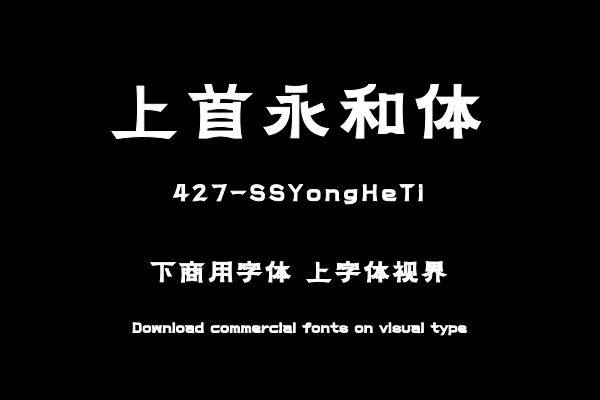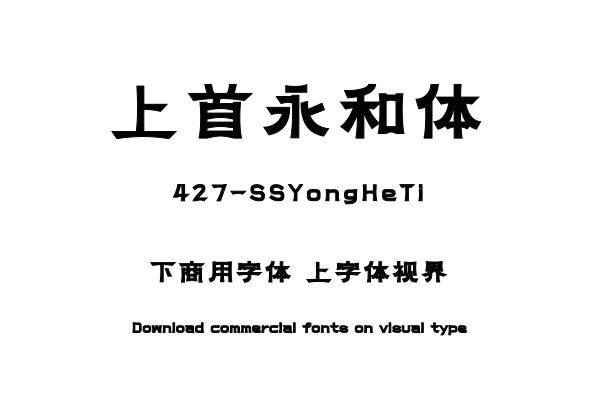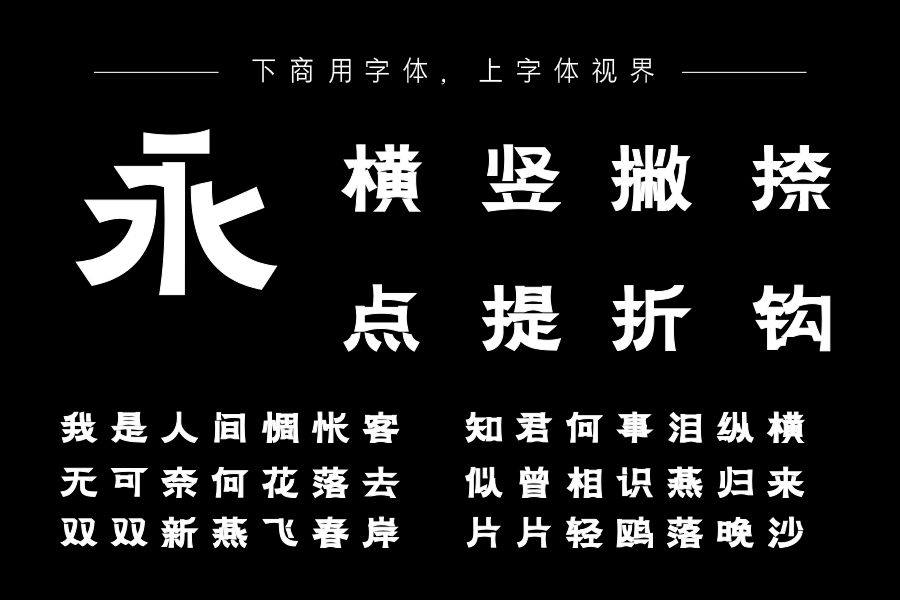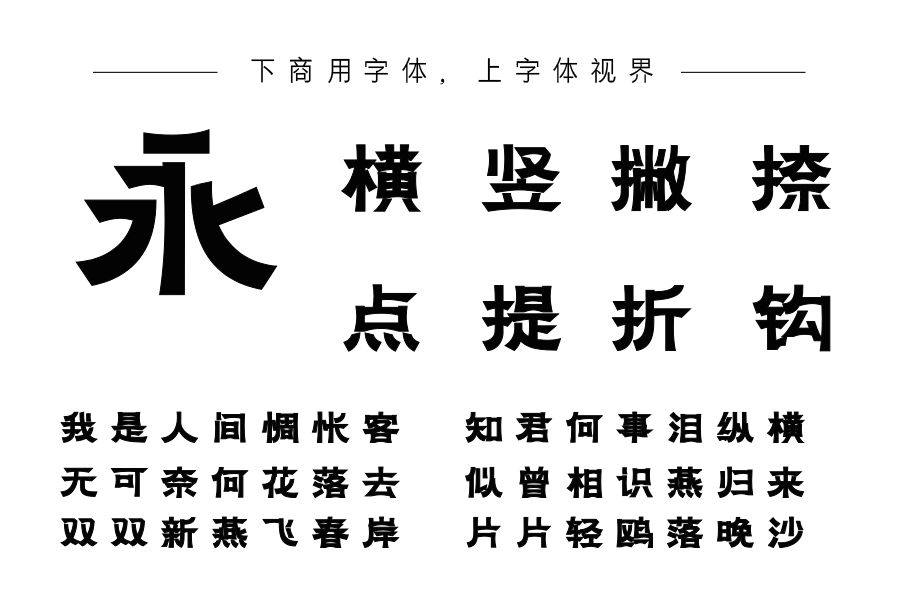
上首永和体,简体中文约6763字,在横笔设计上,采用了 “上直下曲” 的独特形态,同时在横笔的两端做尖角处理,让字体在视觉上更具穿透力。竖笔一侧为挺拔的直线,另......购买须知:“下载服务费”与“字体VIP”所获得字体 仅用于个人非商用, 商用请联系付费授权。本字体为电脑用字,手机没有root权限不支持直接手机换字(手机如何root,请自行百度搜索教程)。购买前请先 了解清楚后再付款 ,字体为虚拟产品无法回收 一旦购买不支持退款。